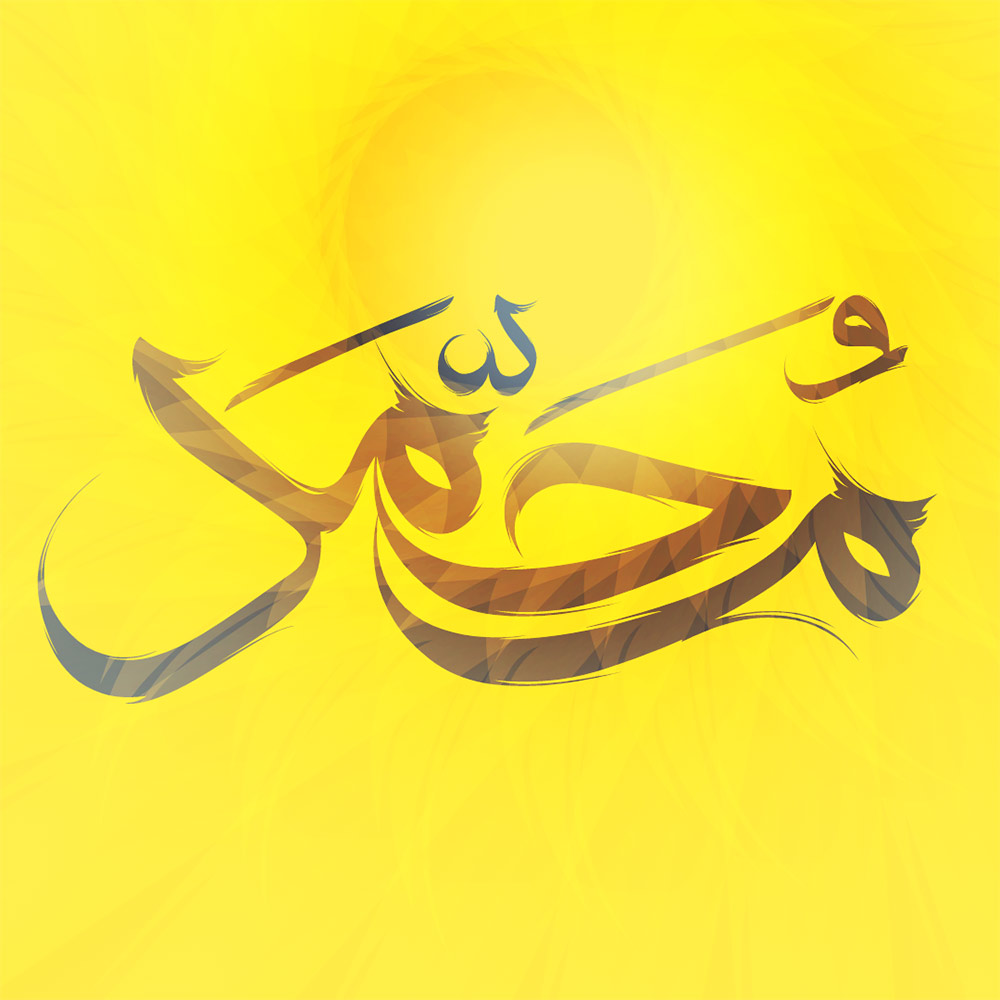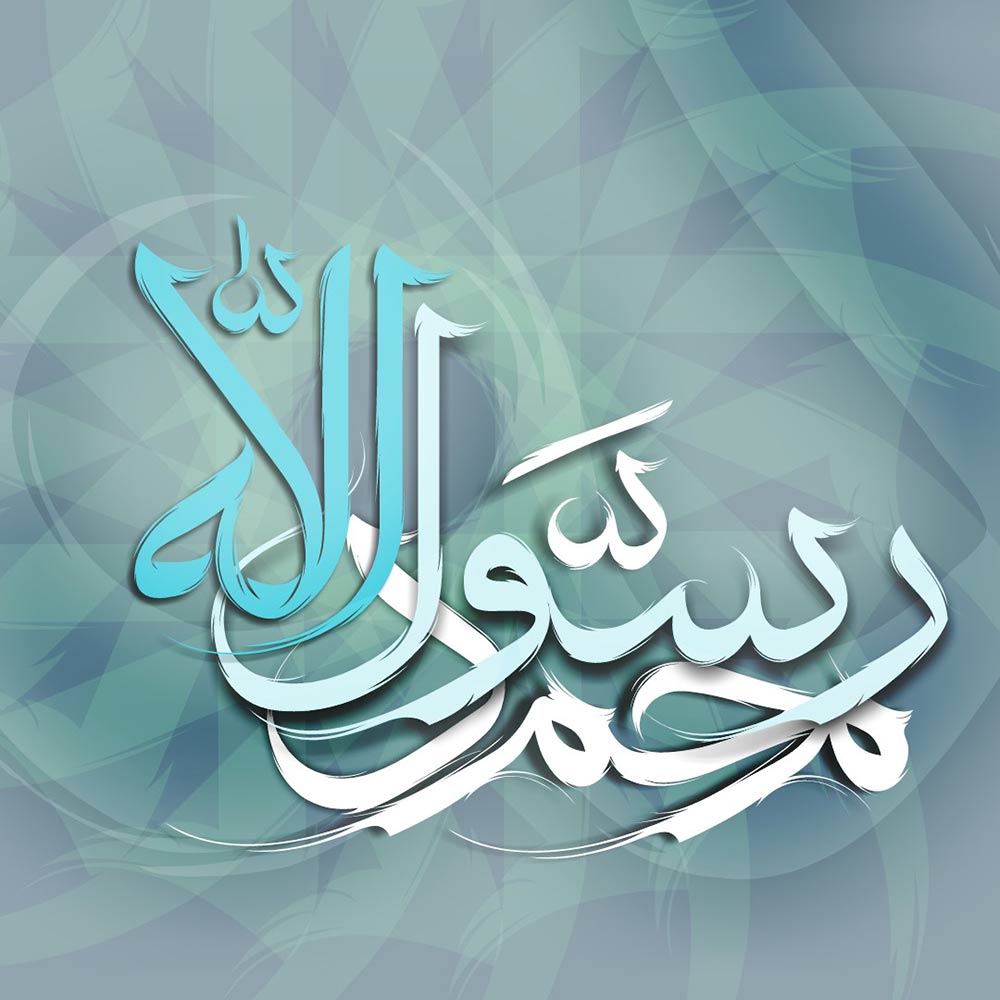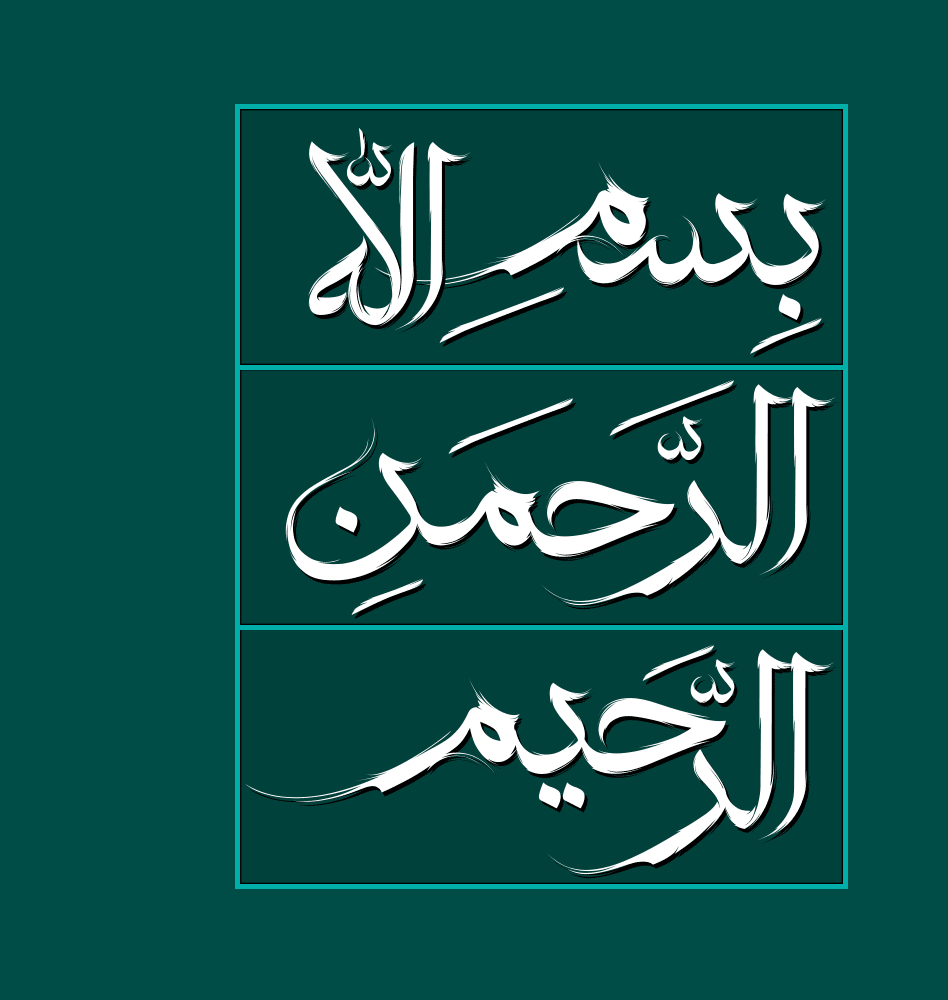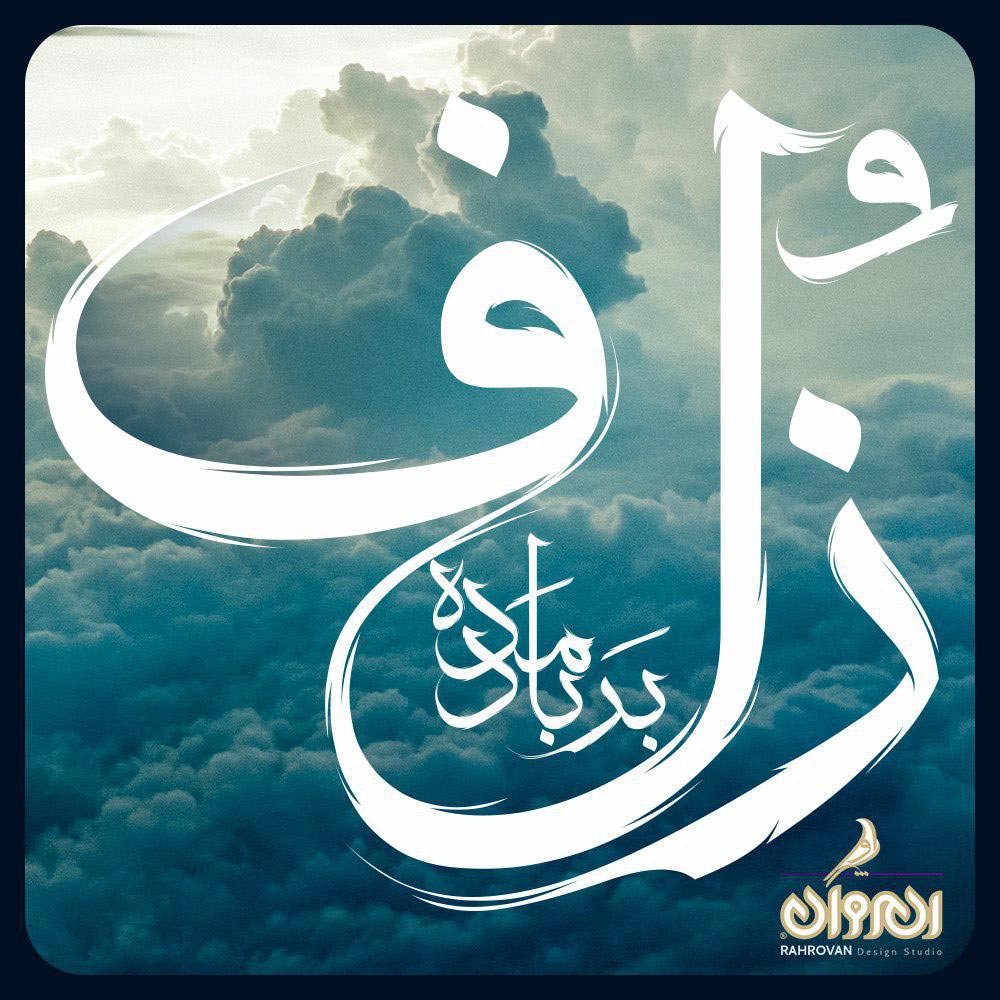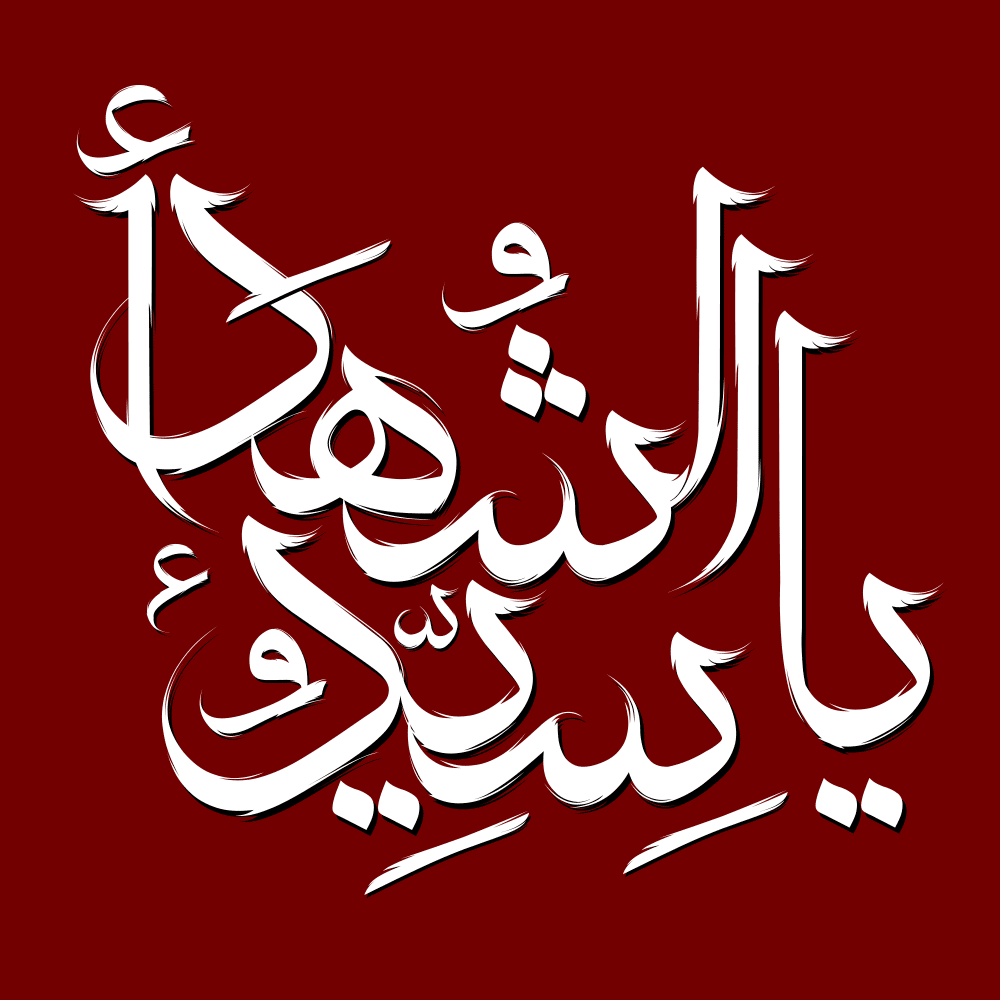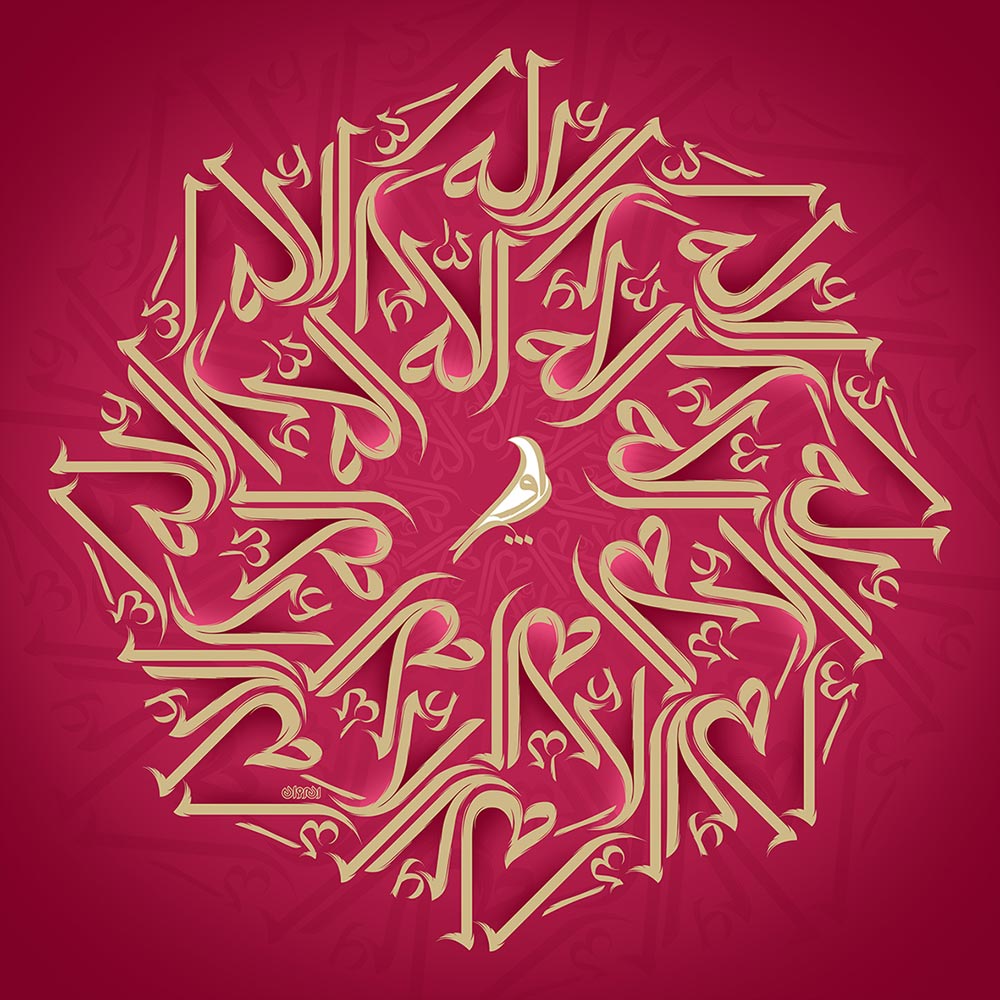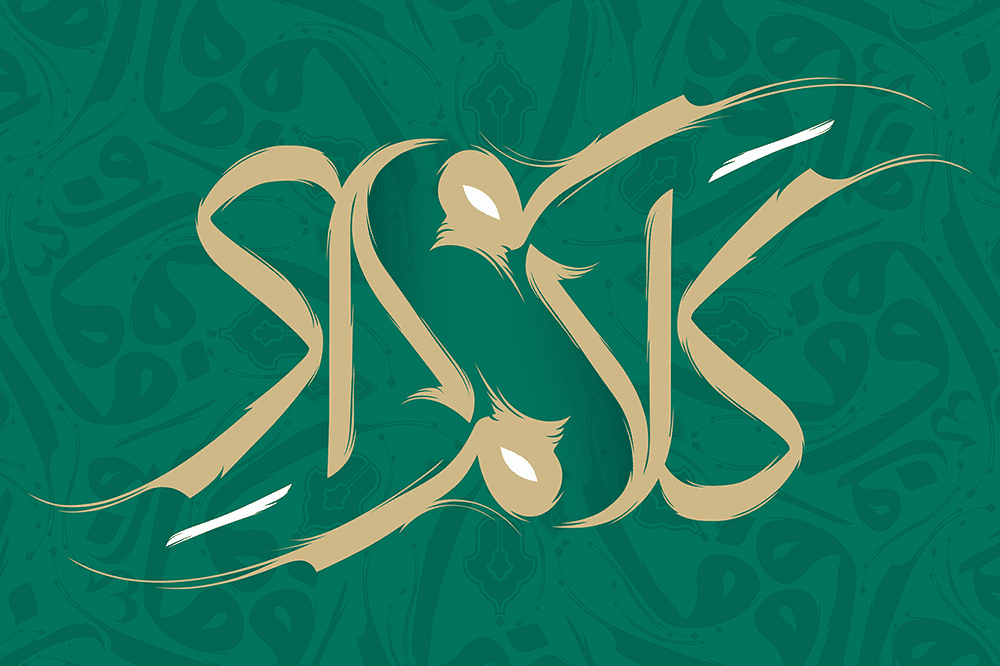
تایپ فیس رهروان با طراحی ابوالفضل رهروان طراح با سابقه ساخته شده است. این حروف معمولاً خارج از سیستم و قواعد فونت‌های مرسوم به یکدیگر متصل و بیشتر بر اساس خلاقیت شخصی ایجاد می‌شود.
فونت رهروان
آقای ابوالفضل رهروان در رابطه با قلم رهروان می گوید:
فونت رهروان بر پایه ی خط ثلث طراحی شده و سعی شده با حفظ روحیه خوشنویسی، فضای بصری جدیدی از این خوشنویسی اصیل به نمایش در آید.
نتیجه کار فونتی رها و هماهنگ است که می توان بوسیله آن تایپوگرافی های جذاب و متفاوتی ایجاد کرد.
فرم های رها و خطوط ظریف در ترکیب با بدنه ی حروف باعث می شود کاربرد این فونت در ابعاد بزرگ، جلوه ای ویژه و منحصر به فرد را نمایش دهد.
رهروان طراح با با تجربه این قلم است که سال‌هاست در آثار خود از حروفی استفاده می‌کند که معمولاً خارج از سیستم و قواعد فونت‌های مرسوم به یکدیگر متصل می باشند و بیشتر بر اساس خلاقیت شخصی این طراح ترکیبات ایجاد می‌شود.